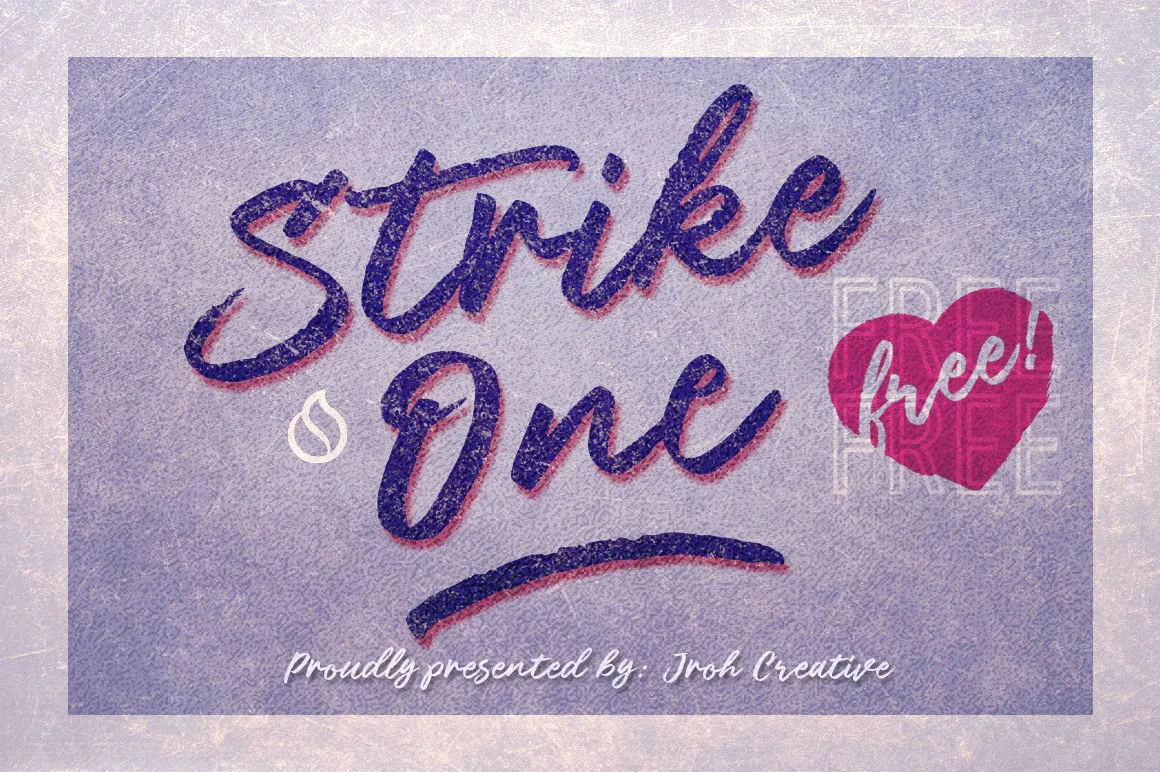
Strike One Script Font – Download Grátis
Através da Jroh Creative apresentamos Strike One Script Font, uma nova opção para quem busca criar texturas agradáveis e estilizadas. Esta font é perfeita tanto para projetos pessoais quanto para trabalhos de clientes. Strike One Free é agora ainda mais completo com características do tipo OpenType que incluem ligaturas padrão, alternativas contextual e 11 swashes. Este conjunto versátil e sofisticado oferece a liberdade para criar texturas vibrantes em qualquer aplicação gráfica. Seja em logotipos ou rótulos de embalagens, tags ou camisetas, até mesmo nas maquetas publicitárias – Strike One Script é uma escolha inteligente para quem busca personalidade e elegância na sua identidade visual.